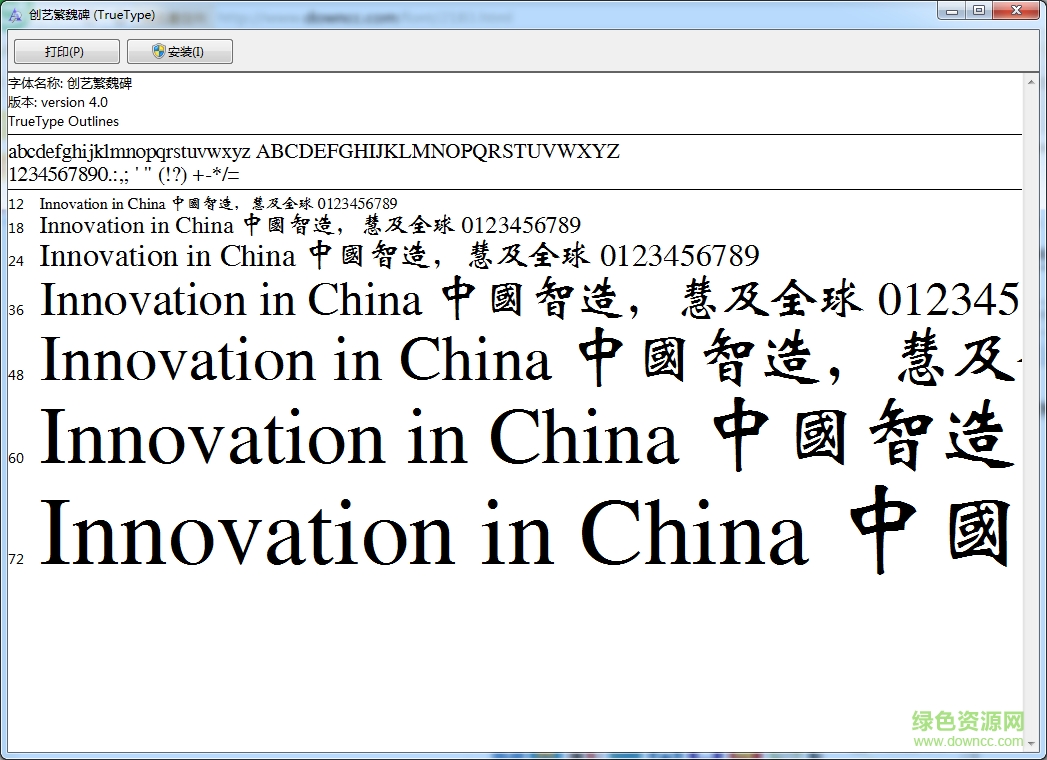
創(chuàng)藝繁魏碑是一款非常好用的繁體電腦字體軟件,字體清秀,略帶圓潤的感覺,使用流暢,快速安裝即刻使用,非常便捷??靵砭G色資源網(wǎng)下載體驗吧!
創(chuàng)藝繁魏碑是一款應(yīng)用于廣面平面設(shè)計方面的繁體中文字體,該字體一筆一畫非常正規(guī),字形端正大方得體,整體效果非常出眾,可以廣泛應(yīng)用于平面設(shè)計、廣告設(shè)計、報紙雜志、正文標題等領(lǐng)域,喜歡的網(wǎng)友可免費下載收藏。